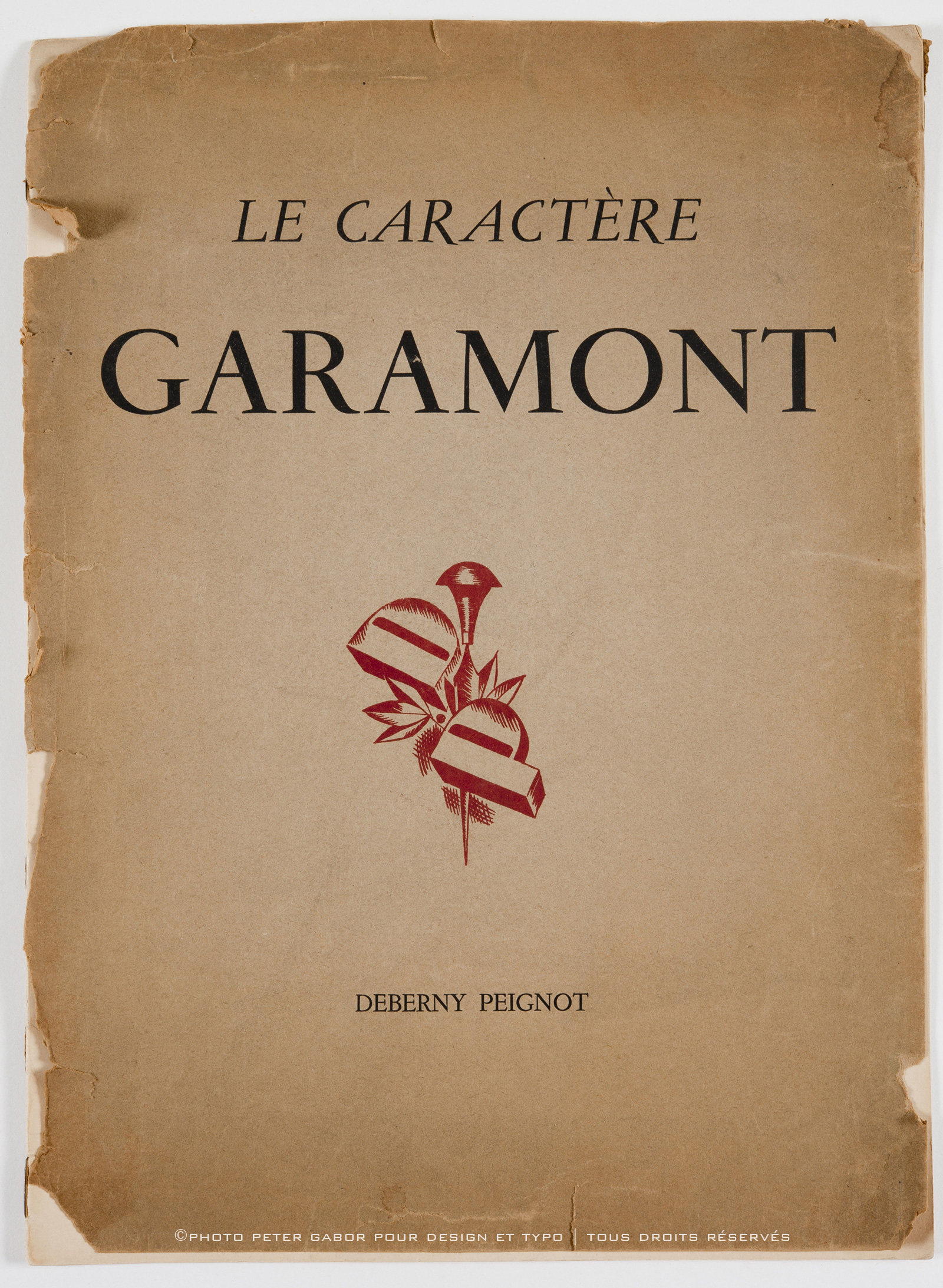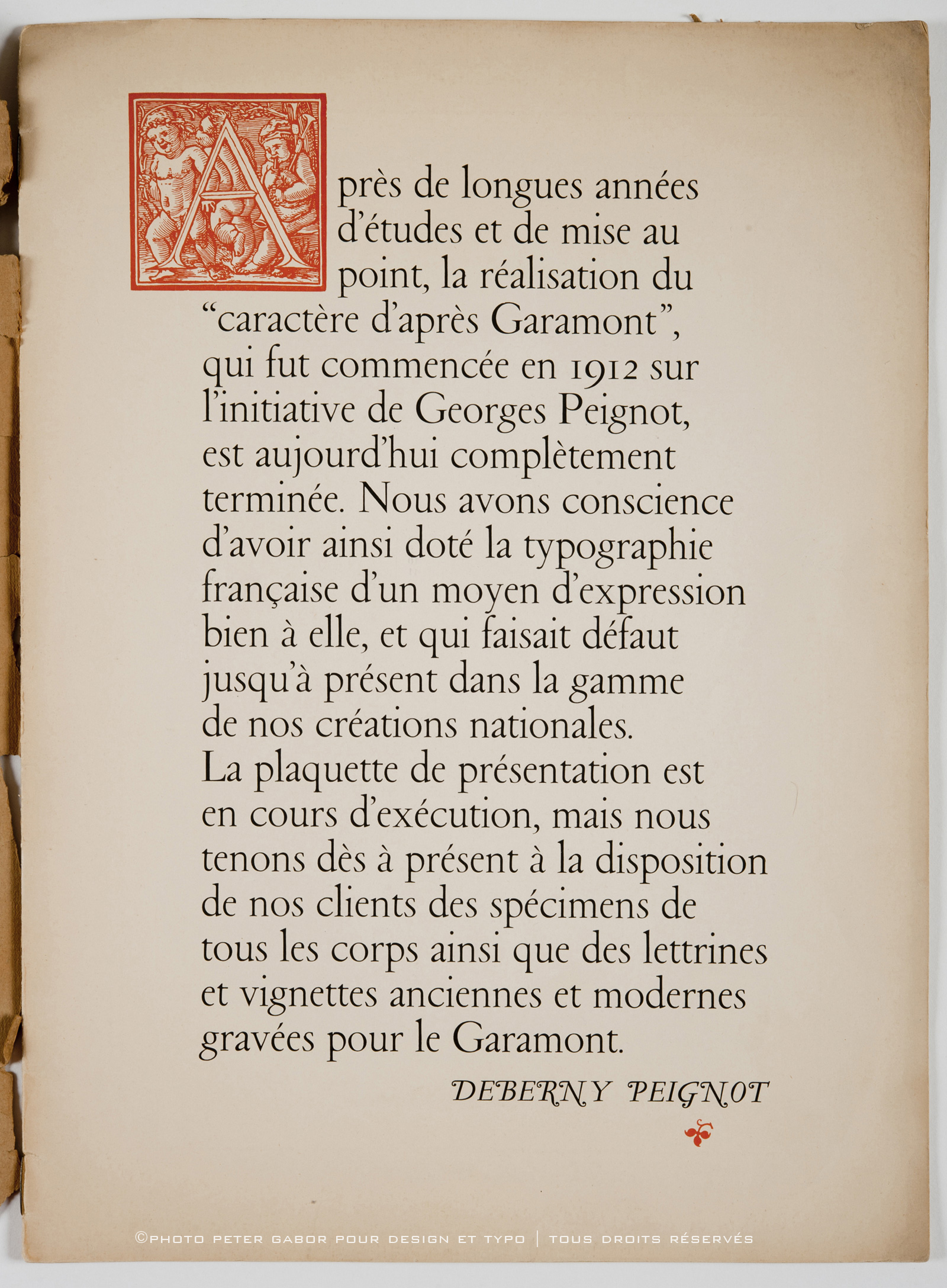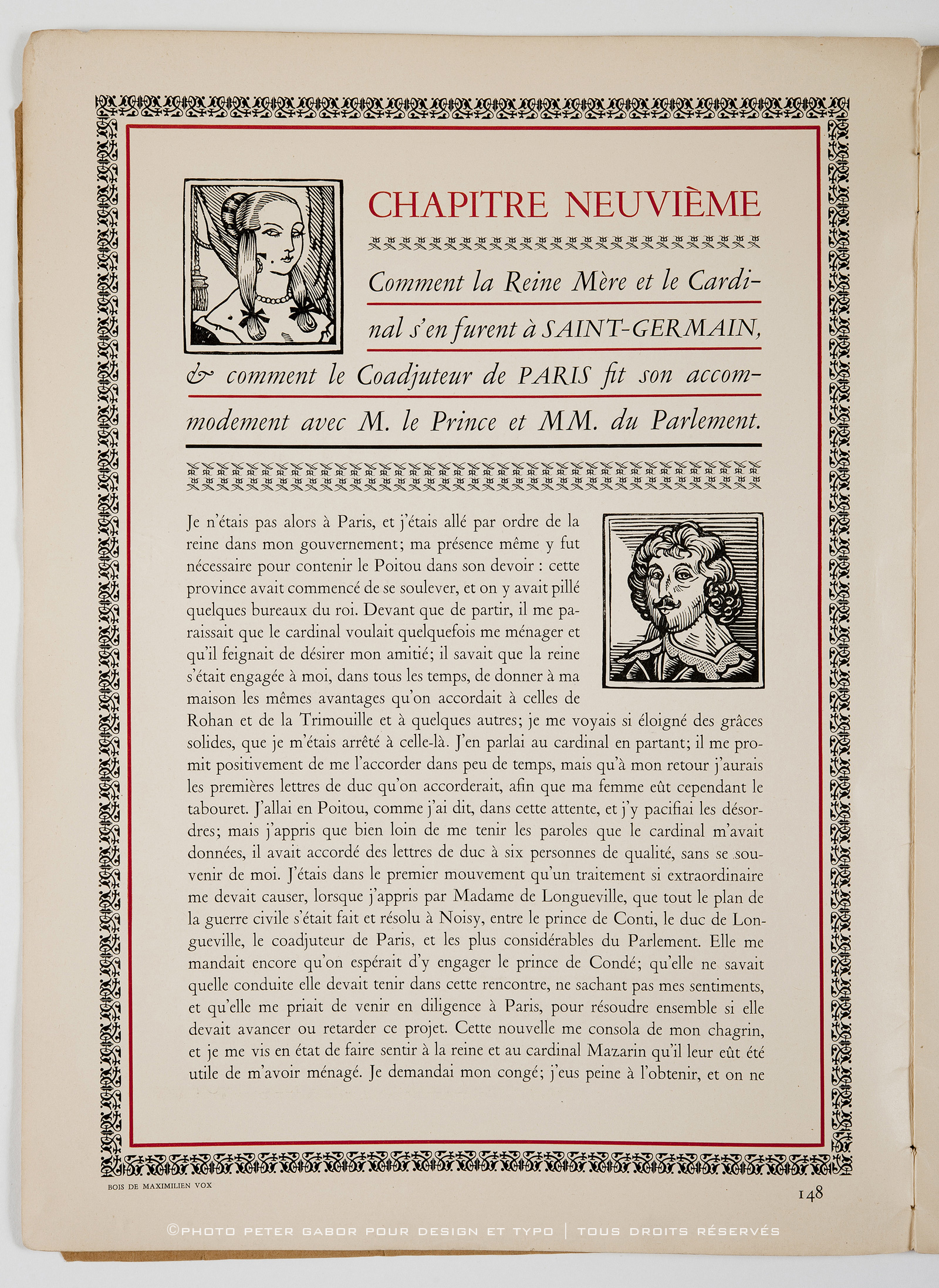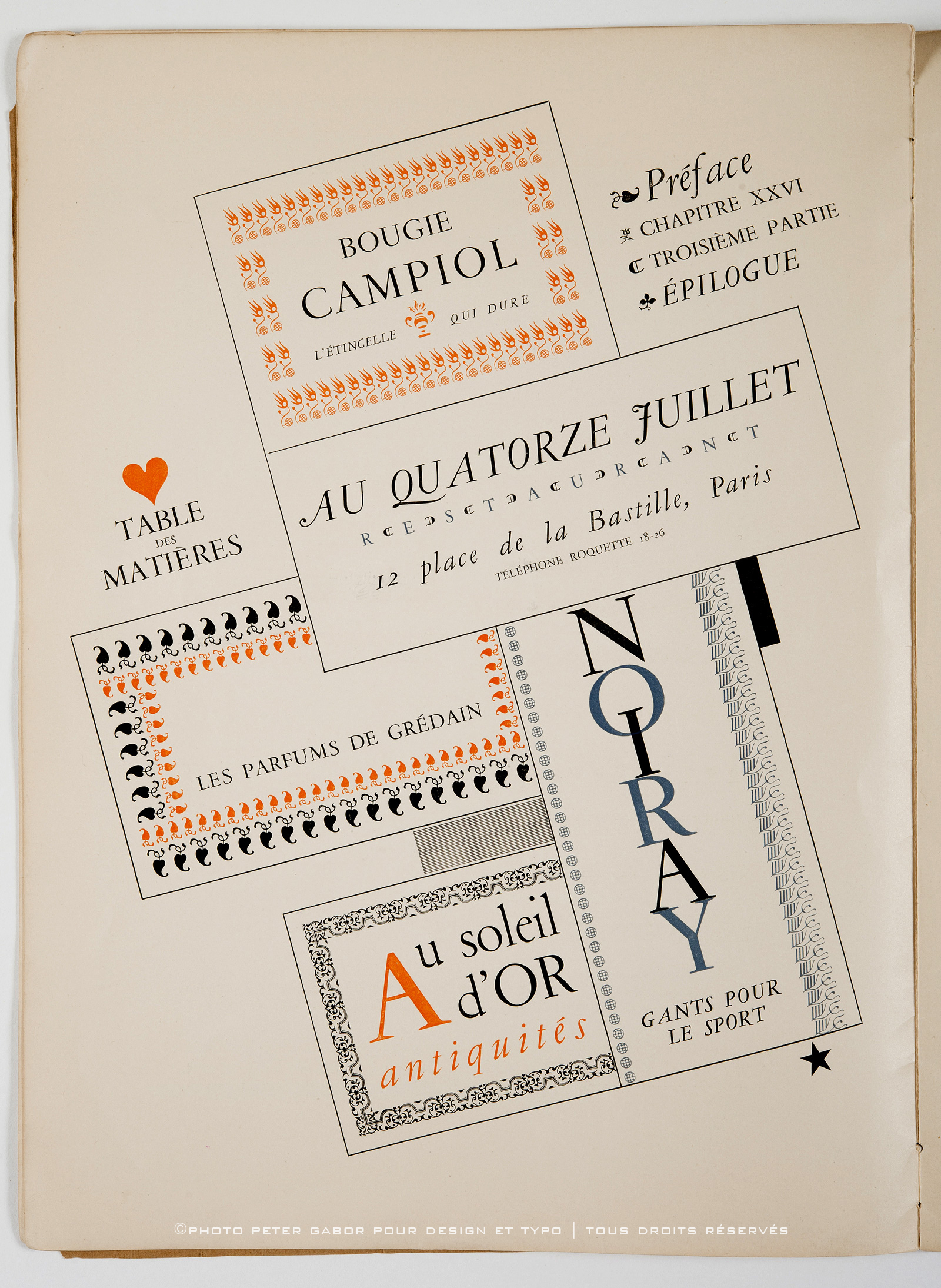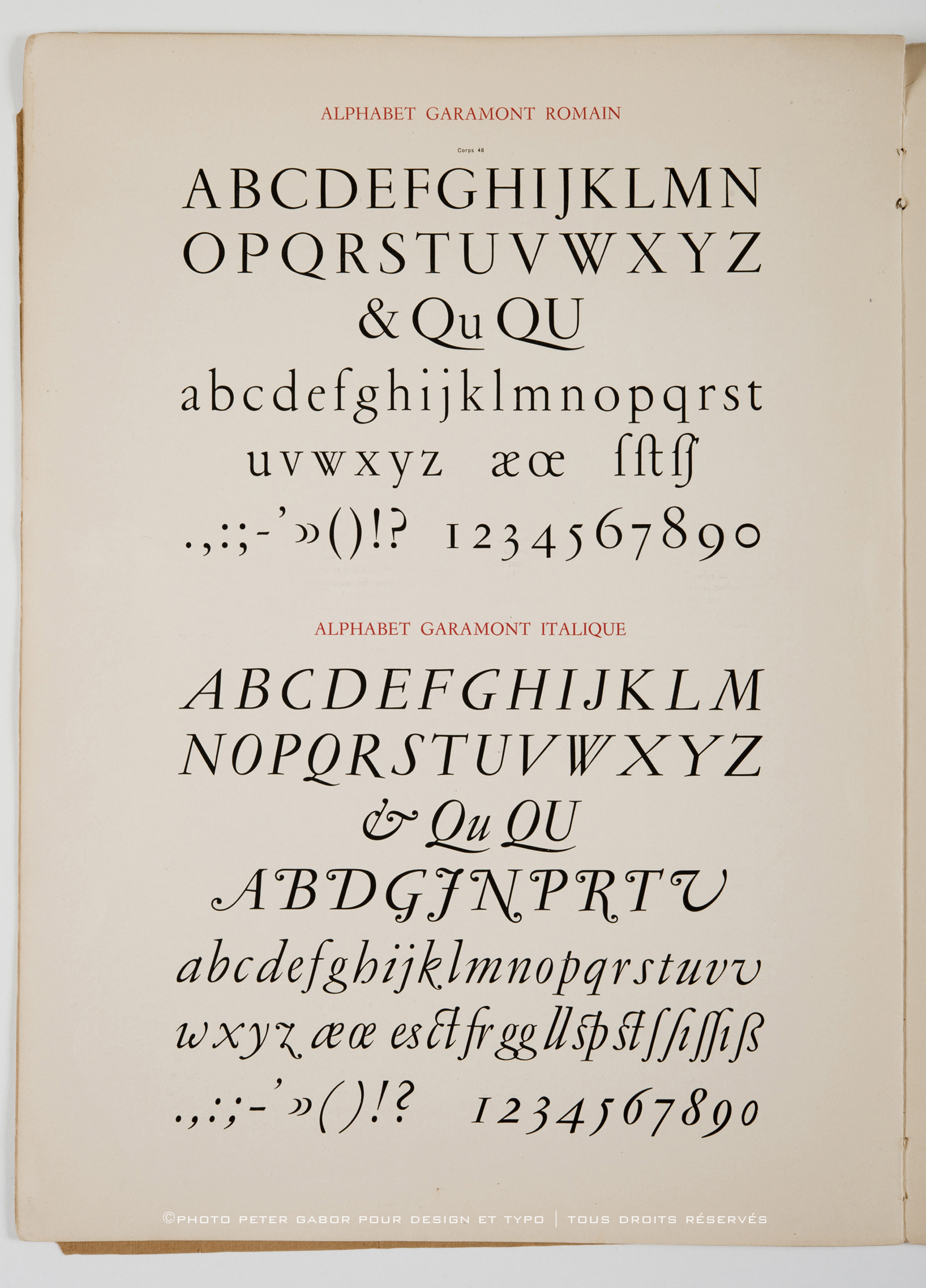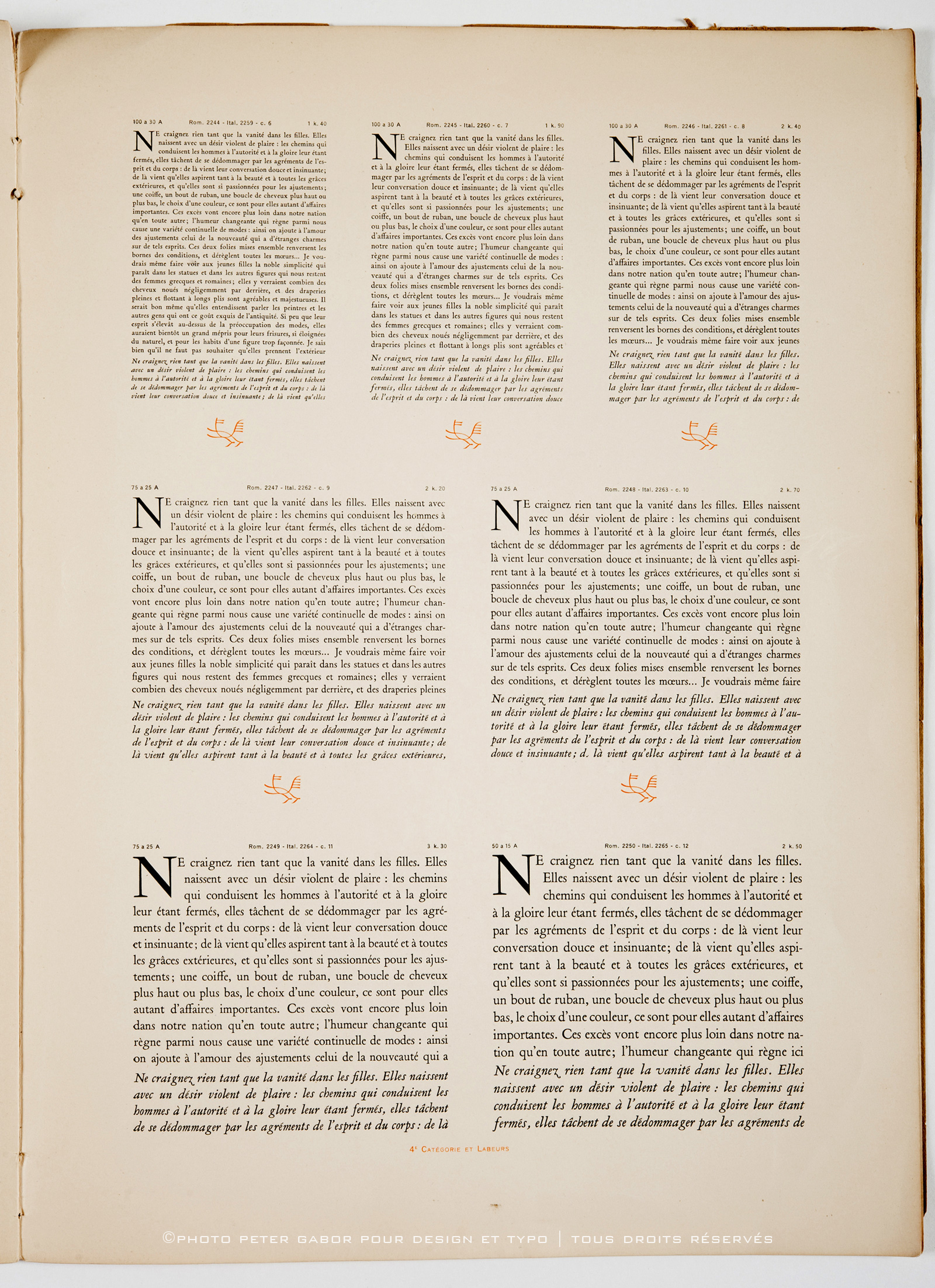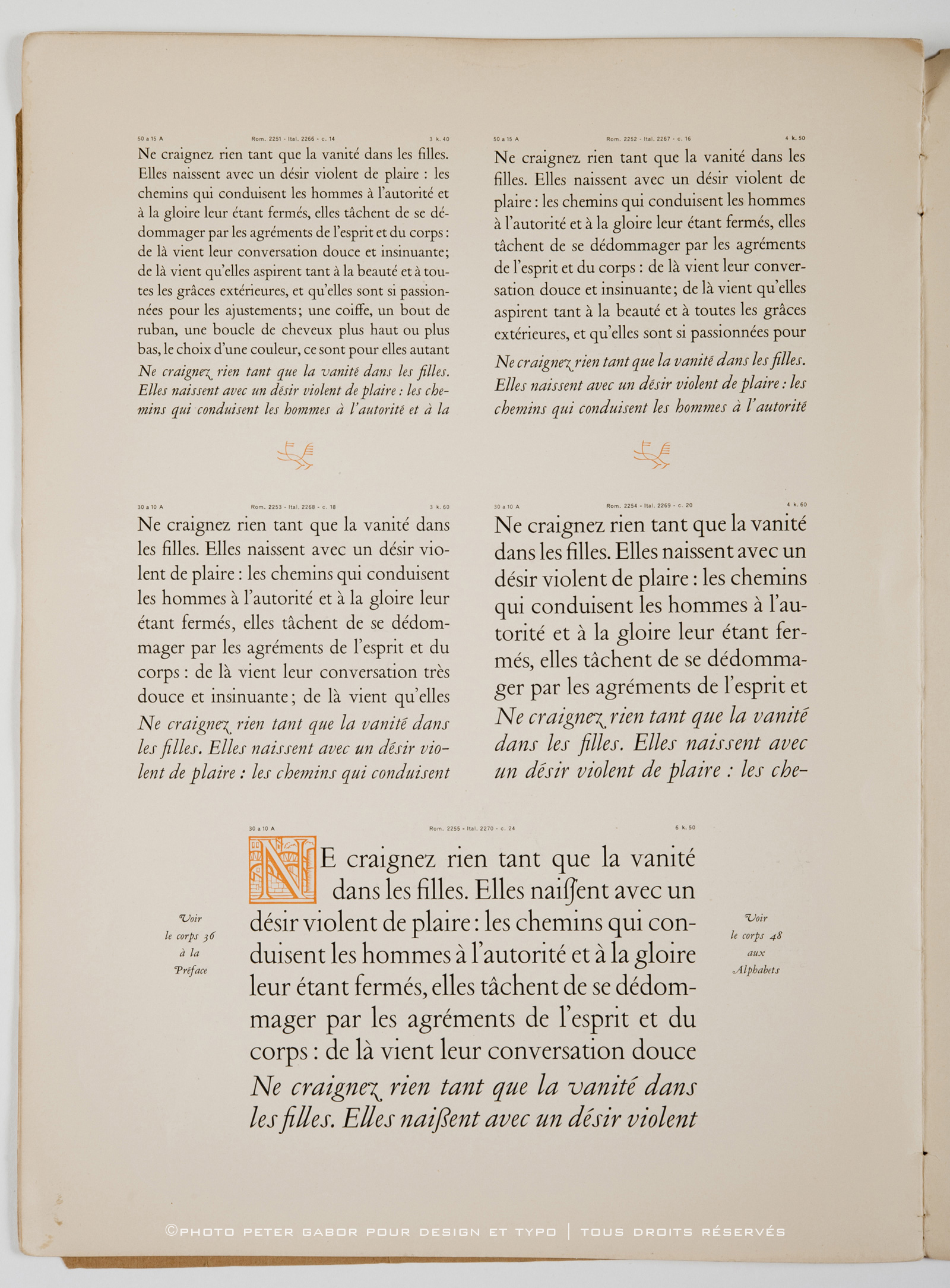
C’est une longue histoire que cette affaire du Garamond. J’avais déjà consacré un billet assez spectaculaire à la question ici. Un comparatif des Garamond de plusieurs fonderies. Celui de Deberny et Peignot n’est pas juste une épisode. D’abord parce c’est la version la plus “Française” d’un caractère né au XVIe siècle et qui va se propager dans le monde entier chez les Allemands (Stempel, Berthold), chez les Anglais (Monotype), chez les Américains avec la Garamond ITC d’abord puis les deux ou trois versions d’Adobe (la Garamond Three, Adobe Garamond etc.)
Ainsi commence l’avertissement au lecteur du présent document:
“Après de longues années d’études et de mise au point) la réalisation du “caractère d’après Garamont”) qui fut commencée en 1912 sur l’initiative de Georges Peignot) est aujourd’hui complètement terminée. Nous avons conscience d’avoir ainsi doté la typographie française d’un moyen d’expression bien à elle) et qui faisait défaut jusqu’à présent dans la gamme de nos créations nationales. La plaquette de présentation est en cours d’exécution) mais nous tenons dès à présent à la disposition de nos clients des spécimens de tous les corps ainsi que des lettrines et vignettes anciennes et modernes gravées pour le Garamont.”
Prenez tout de même le plaisir de venir ainsi à la rencontre de cet alphabet mythique se terminant avec un “d” ou un “t”.